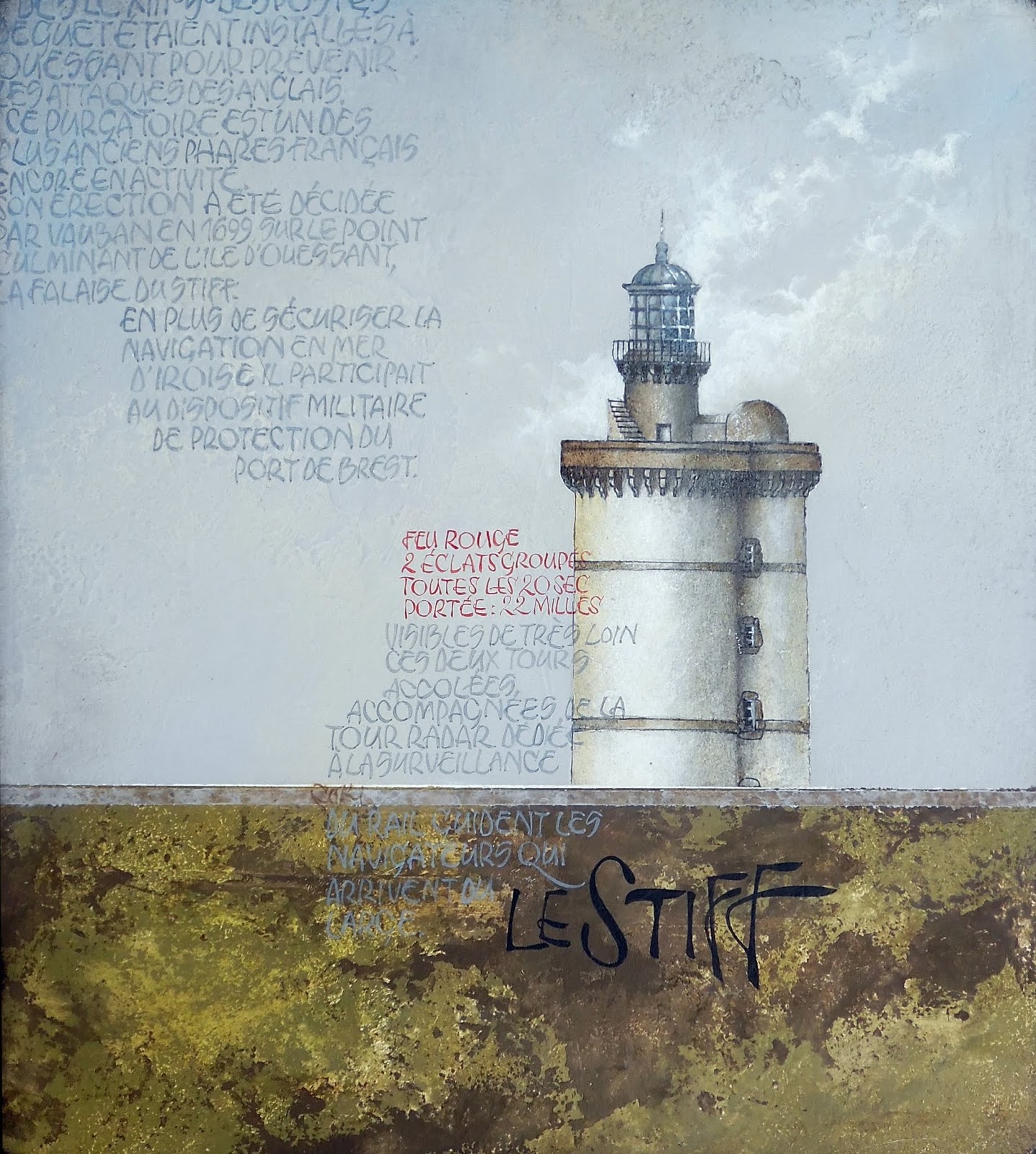
Toile léthale...un CO.RI...calligraphié
La collaboration entre Jean-Noël Riou et moi continue sur le mode calligraphique.
Sur un fond en medium enduit, finement gravé de toiles à la pointe sèche puis travaillé aux pigments, j'ai posé le texte au pinceau pointu.
A son tour, le pinceau de Jean-Noël a révélé la toile en la perlant de gouttes miroitantes, et installé la maîtresse en son centre.
En nouant mon fin fil de salive
j'étale ma toile léthale
et j'emballe mes proies ét...ourdies.
Piège de dentelle ... sur album pinceau pointu
Après des recherches sur brouillon, j'ai posé cette calligraphie préparatoire d'un tableau sur medium, dans mon album "Pinceau pointu". Elle est réalisée avec de la gouache Linel avec un petit pinceau pointu à sortie longue de chez Sennelier.
La calligraphie est basée sur des appuis, des pivots pour produire des pleins charnus et des déliés. Le tracé est lent et attentif. Les formes subissent l'influence des recherches sur le monocondyle que j'avais menées fin août en préparation du stage de Stéphanie Devaux, mais empruntent aussi à l'anglaise.Cette mise en place a précédé la calligraphie du texte sur un fond aux pigments sur medium.
Mise en place calligraphique....Then, my Queen....
Pinceau plat Galaxy 6 mm, huile sur papier esquisse, lettre d'inspiration gothique personnalisées, recherche et mise en place pour un tableau calligraphique.
Texte de Shakespeare, in "A Midsummer Night's Dream" (Le songe d'une nuit d'été )
…. et parce que les essais servent à évacuer les erreurs, les anglicistes auront corrigé : "the night's shade" et non "sad".
Bastaing : Les alouettes
Technique : bois de récupération enduit (enduit coloré bleu doux), pigment blanc de titane, transfert de texte, calligraphie en gris de Payne au pinceau pointu Raphaël 8408 n°4 en poils de martre.
Vous pourrez regarder de plus près notre série des phares, mais pas que…